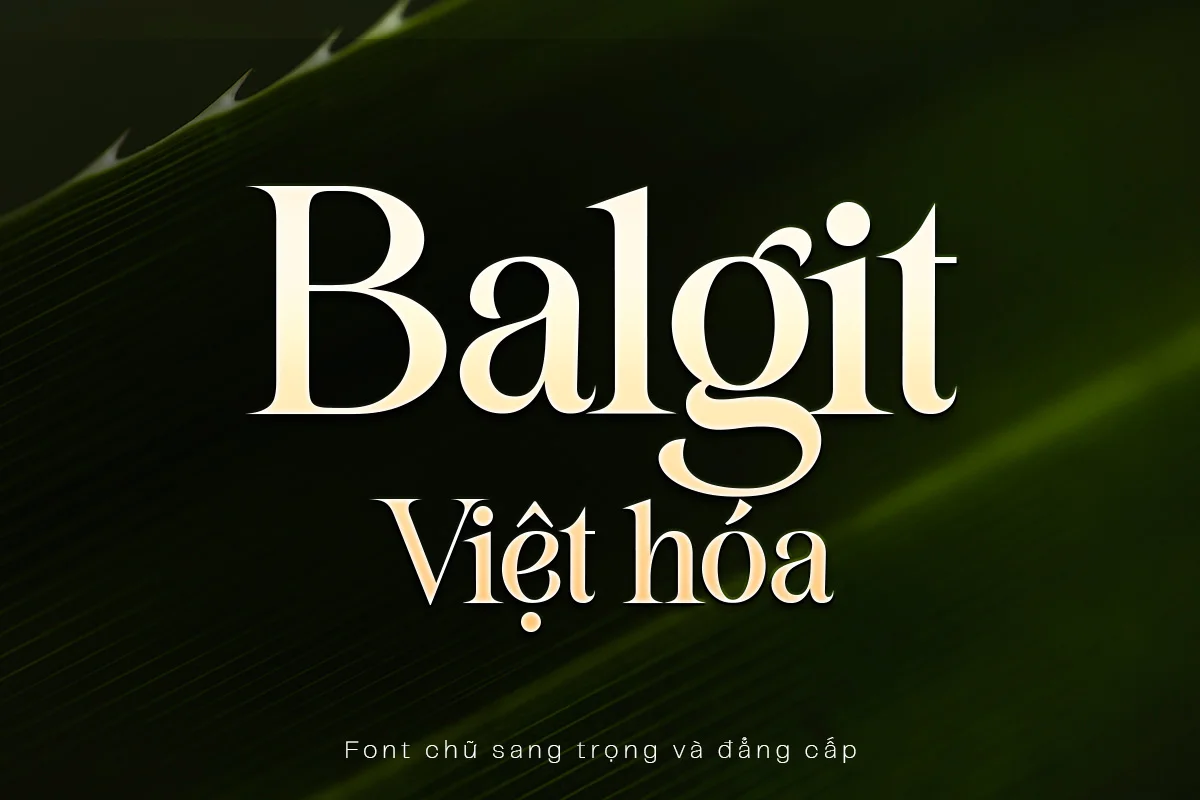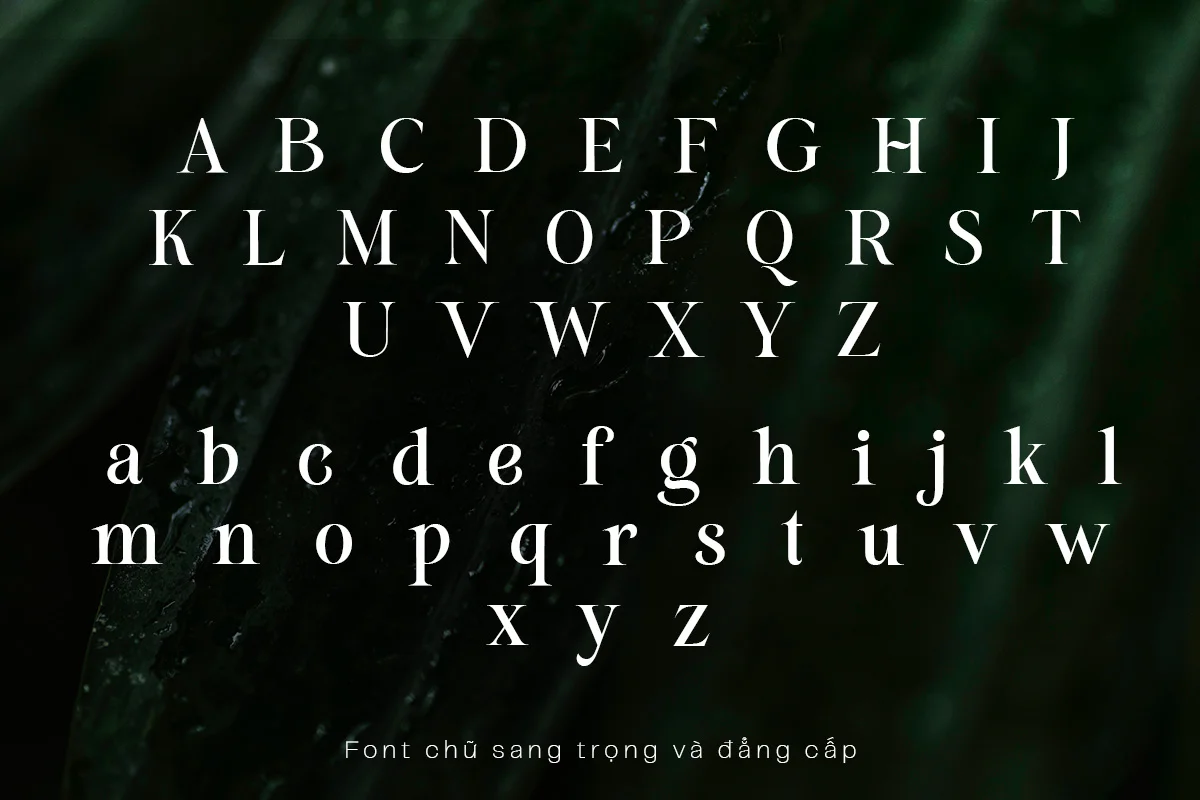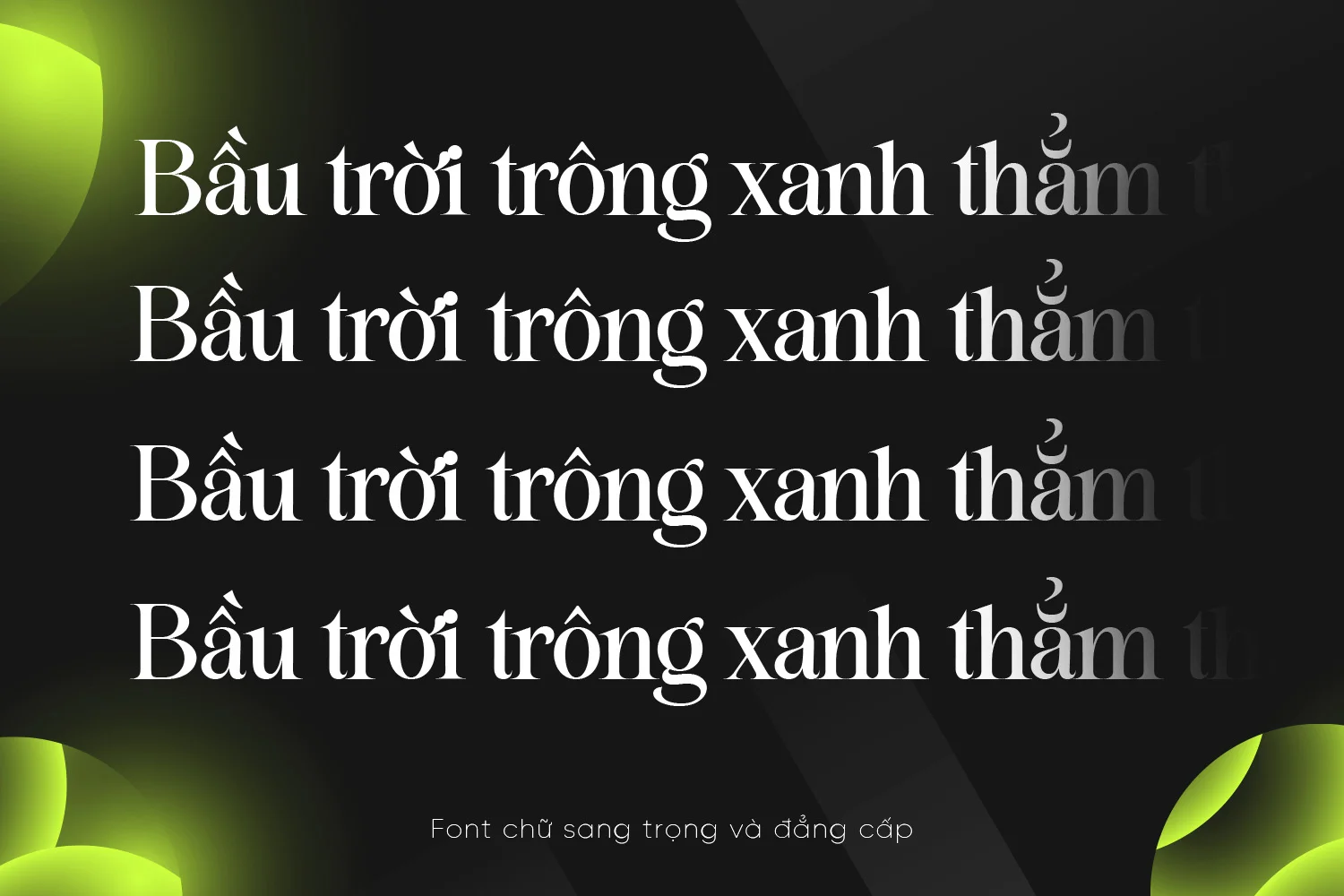
DVN Balgit Việt Hóa là một font chữ serif cao cấp, toát lên vẻ đẹp cổ điển đậm chất quý phái và tinh tế vượt thời gian. Với thiết kế chữ cân đối, đường nét mảnh mai nhưng đầy sức hút, font này trở thành lựa chọn hoàn hảo cho các dự án thương hiệu sang trọng, bìa sách nghệ thuật, thiệp cưới tinh xảo, poster thời trang đẳng cấp hay tiêu đề tạp chí thời thượng. Các ký tự được Việt hóa một cách kỹ lưỡng, sở hữu dấu tiếng Việt rõ ràng và sắc nét, đảm bảo tính ứng dụng linh hoạt mà vẫn giữ nguyên vẻ thẩm mỹ tinh tế. DVN Balgit là biểu tượng của phong cách tối giản hiện đại, mang đến khí chất thanh lịch và uy quyền cho mọi thiết kế sáng tạo.